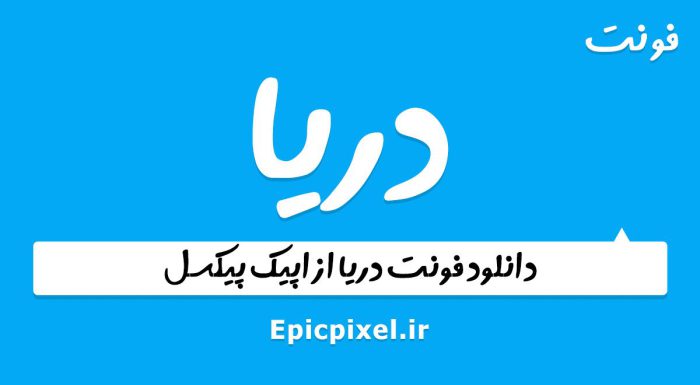
فونت دریا فارسی
دانلود فونت Darya فارسی Font دریا رایگان |
| فونت | فونت دیجی دریا بولد ضخیم Font Digi Darya Bold Bold |
این فونت جهت اعتماد سازی در برندینگ میتونه استفاده بشه و خیلی حس خوبی رو به مخاطب انتقال خواهد داد